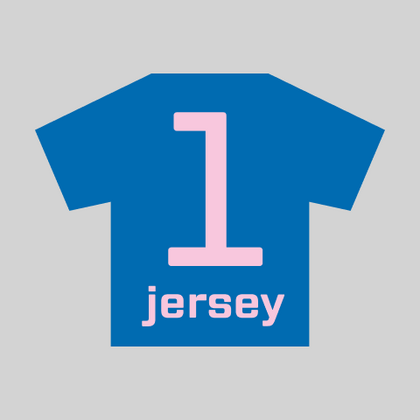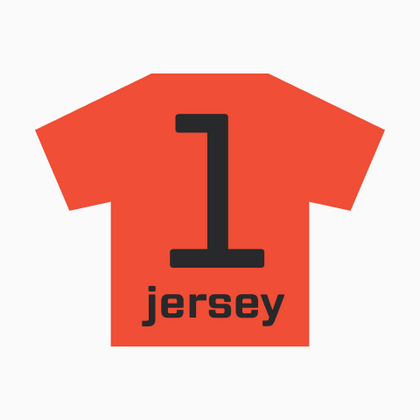
Шрифты для джерси
Это — специально разработанные гарнитуры с динамичным и спортивным характером. Дизайн шрифтов для джерси сочетает четкие геометричные формы и мощные линии, что делает номера и надписи на форме легко читаемыми даже на расстоянии. Здесь представлены современные шрифты, где каждый символ оптимизирован для нанесения на ткань, сохраняя узнаваемость при любом размере. Такие шрифты не просто функциональны — они становятся частью фирменного стиля команды, подчеркивая ее энергию и боевой дух.
TT Gertika — геометрический гротеск с динамичным характером и танцующим ритмом. Идея шрифта зародилась из леттеринга на американском плакате второй половины 30-х годов.
TT Lakes Neue в версии 2.0 — продолжение геометрического гротеска, вдохновлённого финским функционализмом. Новая версия предоставляет больше возможностей, ведь мы не только увеличили кассовый состав и улучшили шрифт технически, но и доработали его визуальный характер.
TT Rounds Neue — гротеск со скругленными формами. В тонких начертаниях шрифт выглядит довольно минималистично и нейтрально: скругленные окончания штрихов становятся практически незаметными, на первый план выходят плавные линии.
Забудьте всё, что вы знали о TT Smalls, ведь мы перевыпустили шрифт! Оформляйте выразительные заголовки, применяйте в оформлении упаковок или выделяйте текст на сайте.
TT Norms Std Condensed является логическим развитием нашего бестселлера TT Norms Pro. Несмотря на то, что шрифт обладает более узкими пропорциями относительно исходной гарнитуры, он унаследовал классические пропорции знаков, внимание к деталям и дотошную проработку каждого знака в шрифте.
При проектировании TT Mussels мы уделили большое внимание возможности верстать большие массивы текста и можем ответственно заявить, что TT Mussels является редким видом технологических текстовых шрифтов.
TT Polls берет свое начало как современный модульный брусковый шрифт. При создании шрифтового семейства TT Polls мы держали в голове его использование в дизайне на спортивную тематику, но финальная версия TT Polls отлично подходит и для более казуального дизайна и сфер применения.
Первоначально идея шрифтового семейства TT Milks заключалась в том, чтобы создать коллекцию шрифтов для использования в упаковке и брендинге молочной продукции.
TT Octas — шрифтовое семейство с узкими пропорциями, построенное по принципу октагональности, в данной гарнитуре все окружности представляют из себя восьмигранники. Благодаря небольшим засечкам Октас приобретает насыщенный и старинный характер.
Любите ли вы раннюю советскую визуальную культуру как любим её мы? Несмотря на свое советское прошлое, TT Bricks выглядит очень свежим и визуально мощным шрифтовым семейством, которое отлично вписывается в современное медиапространство.
TT Slabs является простой и геометричной брусковой гарнитурой и отлично подойдет вам, если для ваших проектов вы ищете универсальный шрифт с широкими пропорциями.